A resposta lógica não basta. Eu quero mais.
Vou começar a reclamar. Me conte depois, por favor, se já estou rabugento.
Diante de uma turma de estudantes de design, é comum eu perguntar quem deles ouviu falar do David Carson. O meu herói (ou anti-herói) favorito. Para minha surpresa, não importa a universidade, apenas uma ou duas mãos são levantadas. Uma sempre é a do professor.
Quando a palavra “design” foi elevada à diretoria das empresas, sistematizou-se um processo lógico em busca da eficiência máxima. Descobriu-se que é na intersecção entre design, tecnologia e negócios que estão as soluções mais eficazes, que atendem todos à mesa. O consenso, não à toa, tende a ser pouco imaginativo.
O trabalho do Carson é muito mais intuitivo do que racional. Afinal de contas, era um surfista profissional (mesmo, 9º no ranking mundial) com graduação em Sociologia, armado de um computador no boom do desktop publishing. Seu design quebrava todas as regras, e exatamente por isso, marcou uma geração. A difícil legibilidade não o impediu de ser contratado por empresas “tradicionais” como a American Airlines, Audi, Intel e Microsoft. Hoje, em sua Masterclass, ele ensina a criar através de colagens, confiando no instinto, na intuição, e não na razão.
A razão do algoritmo de SEO diz que este texto está péssimo pois a palavra do título não aparece no primeiro parágrafo. Eu deveria dizer logo o que quero dizer. As pessoas não têm tempo para essa enrolação. Vou continuar.
Daqui há 20 anos, você lembrará do design de algum dos sites que visita hoje? Eu lembro de dois, da minha época de internet discada. Um era da 2Advanced, um estúdio extremamente high-tech cuja tecnologia nos deixava de boca aberta. Era um prazer esperar 2 minutos inteiros para ele carregar; o outro, do perspicaz Luli Radfahrer, era um labirinto, literalmente, para você navegar. Inesquecível.
Numa aula, o especialista em copywriting nos entrega de bandeja a estrutura de texto perfeita, a mais eficaz, ditando até a quantidade de argumentos que precisam estar em bullet points e quando eles devem aparecer. E ele tem pesquisas sólidas (de verdade) para embasar essas recomendações. Sabemos que isso funciona.
Resolver um problema com o menor atrito possível é sim a função do design. Dizem que o Carson faz arte, não design. A arte mexe com a nossa emoção, com subjetividade. O design não tem tempo pra isso, tem uma função clara a cumprir. Isso faz sentido no projeto de uma bula de remédios, mas, precisamos separar o design da arte de forma tão brutal? E se incorporarmos mais subjetividade? Adicionar camadas de significado que podem encantar quem as descobrir? Na imagem abaixo, não foi a funcionalidade que fez o pedestre se contorcer para ler este cartaz:
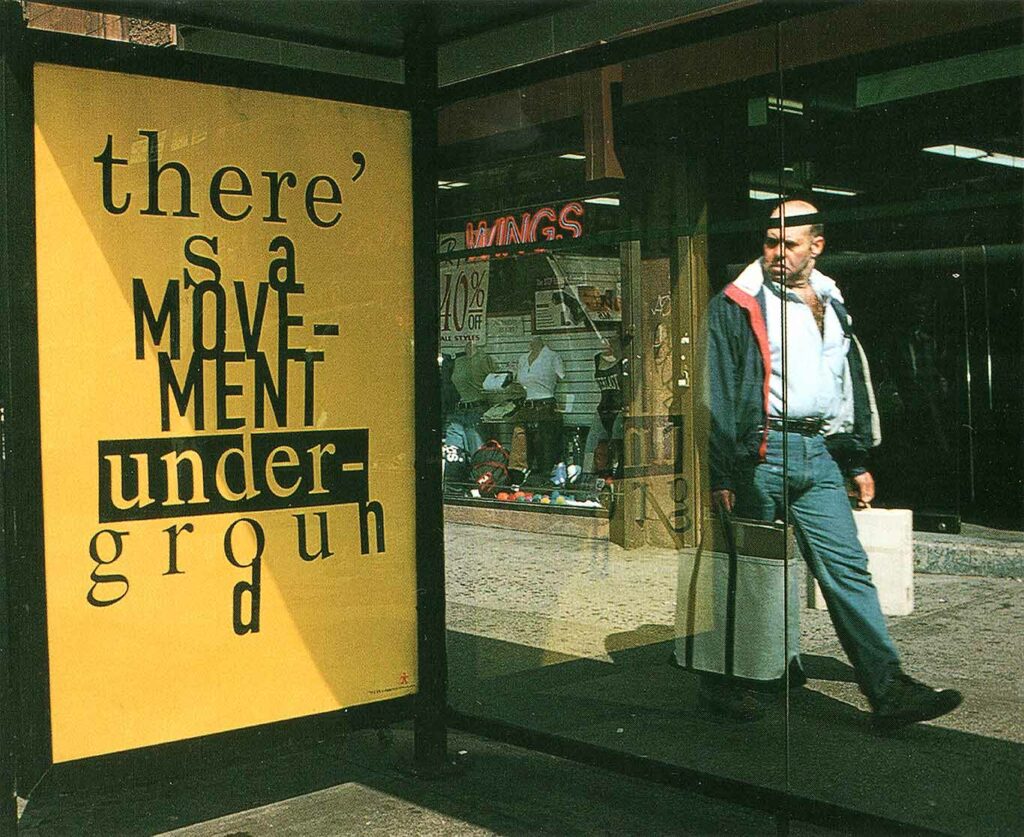
Quando todos os sites tem o mesmo template. Quando os novos produtos são lançados com a mesma fórmula. Quando os funis de venda são todos iguais, explorando os mesmos gatilhos. Quando os logotipos, estilos tipográficos, de ilustração e de ícones seguem as mesmas tendências, seguras, aprovadas pelo consenso, eu me pergunto se não podemos mais. E desconfio que o design memorável é o que já faz exatamente isso.